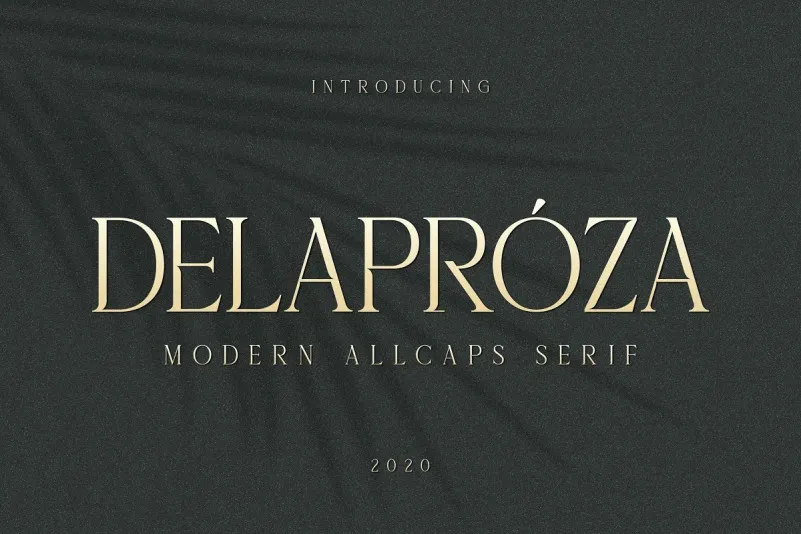
A Delaproza Font é uma elegante escolha para quem busca combinar sofisticação com tradição moderna. Inspirada no famoso logotipo minimalista, essa fonte serif oferece uma estrutura arquitetônica que permite aos designers criar alternativas tanto de design moderno e elegante quanto clássico. Perfeita para a criação de templates, brochuras, vídeos, branding em publicidade, logos ou qualquer projeto que valorize uma estética contemporânea sem renunciar à elegância tradicional. Esta fonte representa um equilíbrio perfeito entre seriedade e simplicidade, ideal para designers buscando expressar seus trabalhos de maneira inconfundível e atraente.